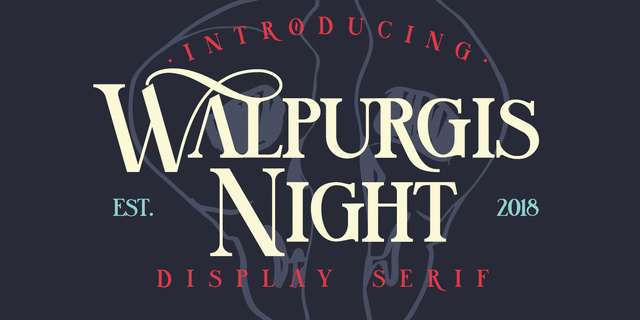
Шрифт Вальпургиева Ночь – это элегантный, винтажный шрифт с засечками, вдохновленный классическими старинными шрифтами. Он прекрасно представляет современную и винтажную эстетику. Шрифт содержит особые заглавные буквы, множество альтернативных символов и красивые лигатуры и росчерки. Шрифт идеально подходит для свадебных пригласительных билетов, дизайна красивой модной упаковки, очень хорош для оформления книг, журналов, брендинга и других дизайнерских задач. Он поддерживает множество языков на основе расширенной латиницы. Чтобы включить альтернативы OpenType Stylistic, вам нужна программа, поддерживающая OpenType фичи, например, Adobe Illustrator, Indesign, Photoshop или CorelDraw X6-X7. Walpurgis Night разработал Андрей Дыкун в 2018 году.
заметный, старомодный, выразительный, дорогой, богатый, аристократичный, торжественный, динамичный, благородный, мастерский, традиционный, качественный, культурный, эстетичный, антикварный, ностальгический, романтичный, старинный, исторический, гордый, серебрянный, театральный, драматичный, ролевой, сложный, вычурный, готичный, закрученный, криповый, оригинальный, характерный, игривый, самобытный, артистичный, интересный, декоративный, колоритный, живой, крафтовый, волшебный, замысловатый, сказочный, ламповый, ремесленный, творческий, колдовской, магический, праздничный, осенний, зловещий, злой, кладбищенский, страшный, адский, странный, причудливый, оккультный, таинственный, загадочный, жуткий, гибкий, горячий, огненный, фантастичный, вампирский, дикий, пафосный, ночной, музыкальный, сексуальный, макабрический
алкоголь, детектив, трофей, награда, антиквариат, театр, опера, литература, вино, ресторан, карты, чай, часы, серебро, драма, романтика, любовь, замок, тату, сувенир, волшебная сказка, меню, хеллоуин, свиток, король, королева, дракон, фентези, кузница, ремесло, украшения, праздник, игра, осень, страшилка, приключения, анимация, сказка, татуировка, хэллоуин, волшебник, колдун, специи, твари, украшение, хоррор, ужастик, развлечения, аттракцион, кладбище, заклинание, магия, проклятие, мультфильм, призрак, привидение, ведьма, Самайн, вампир, монстр, чудовище, мемориал, памятник, виски, коктейль, клуб, ночной клуб, музыка, рок, концерт, легенда, квест, рок-н-ролл, компьютерная игра, графика, иллюстрация Стилистика: